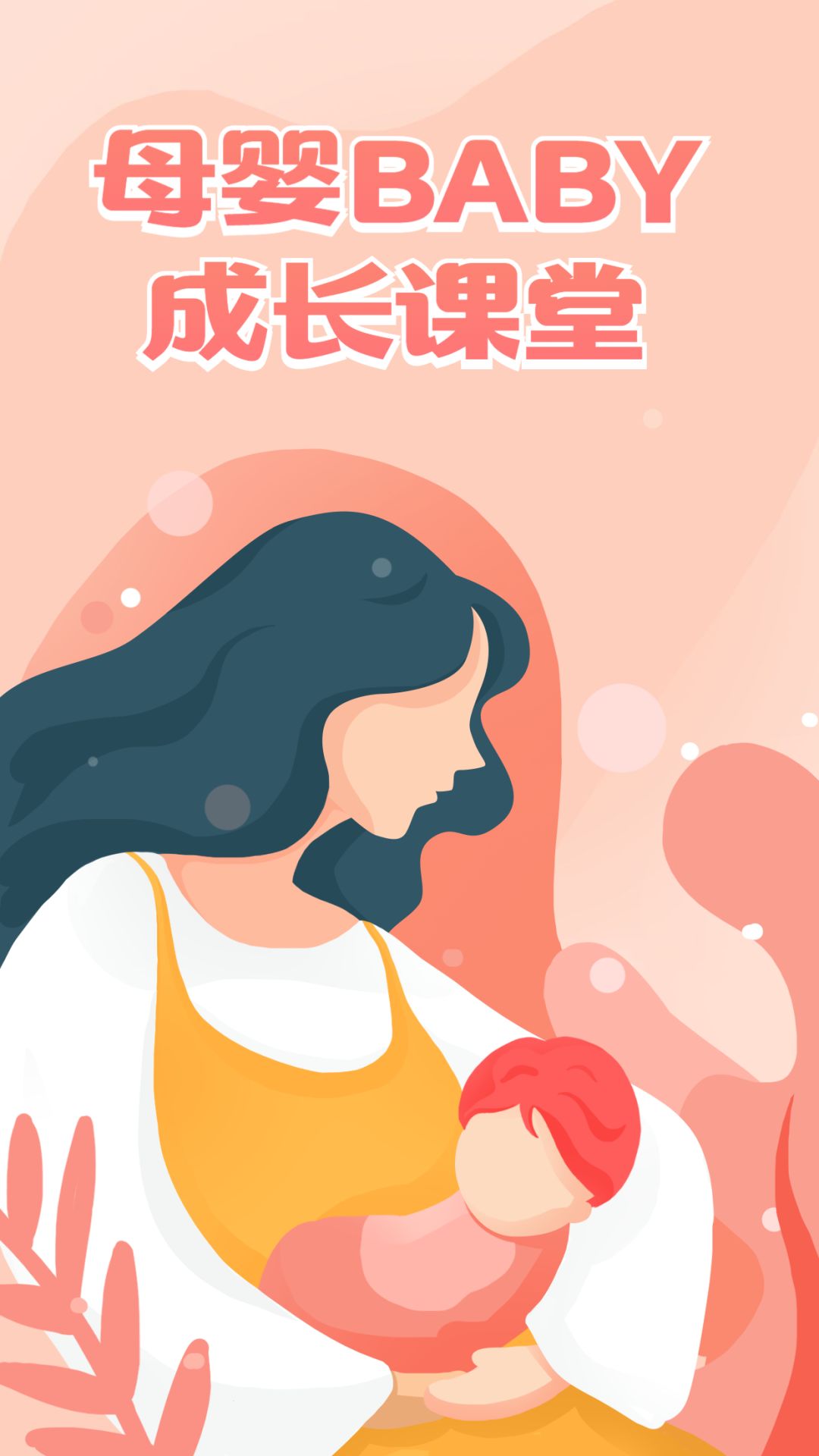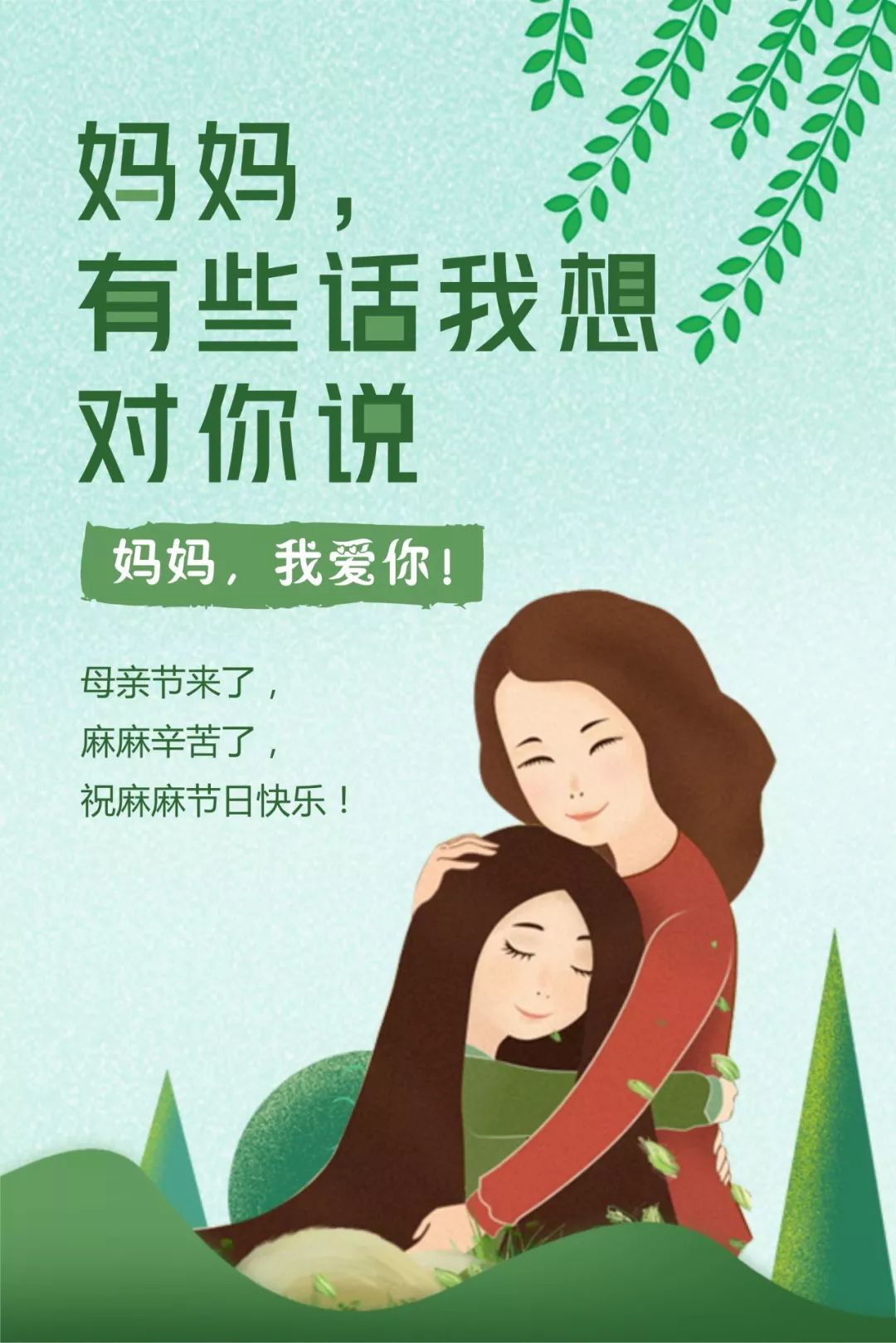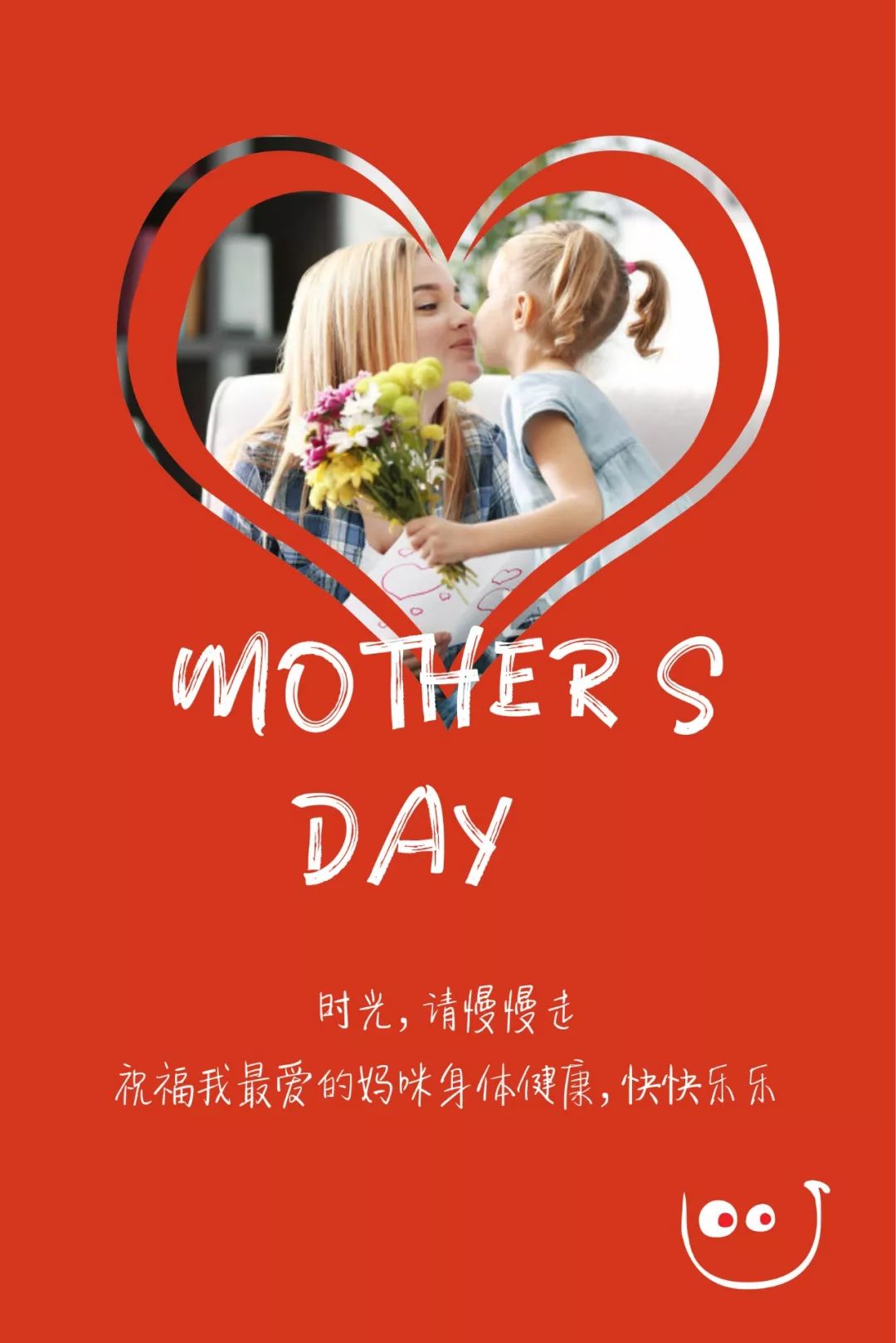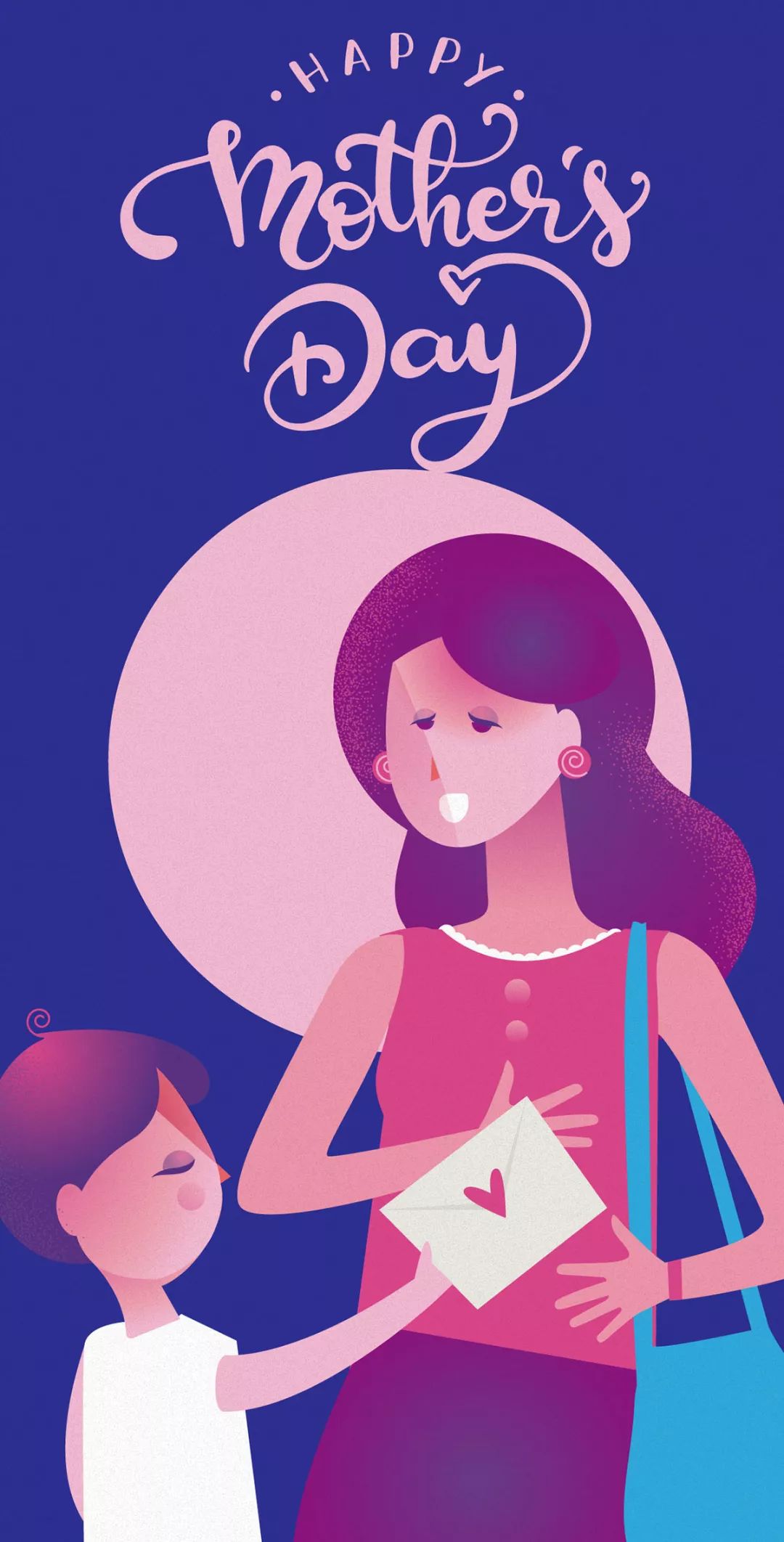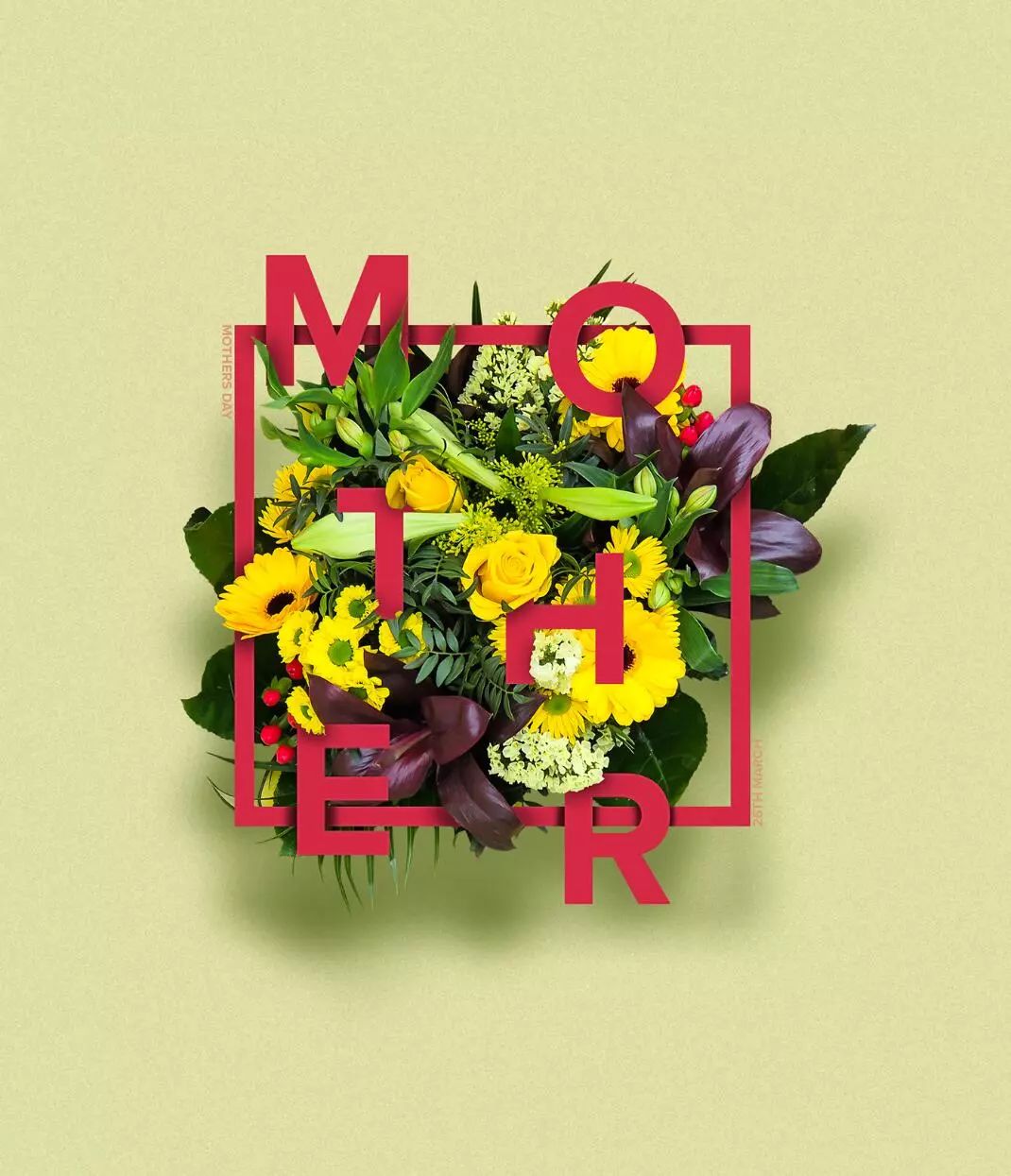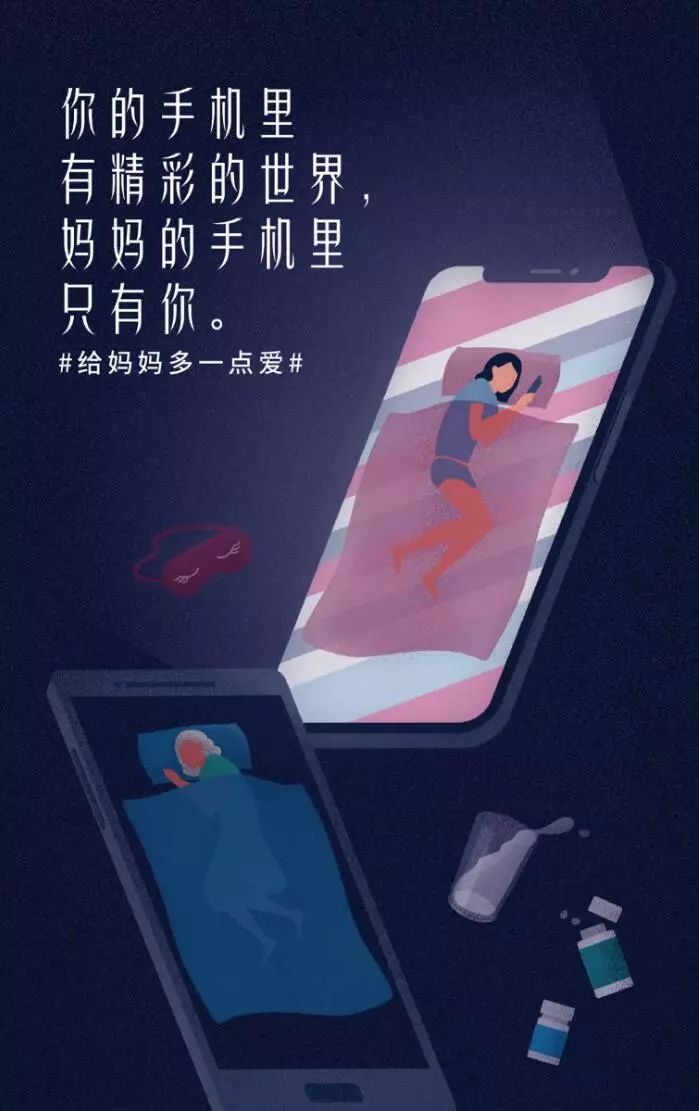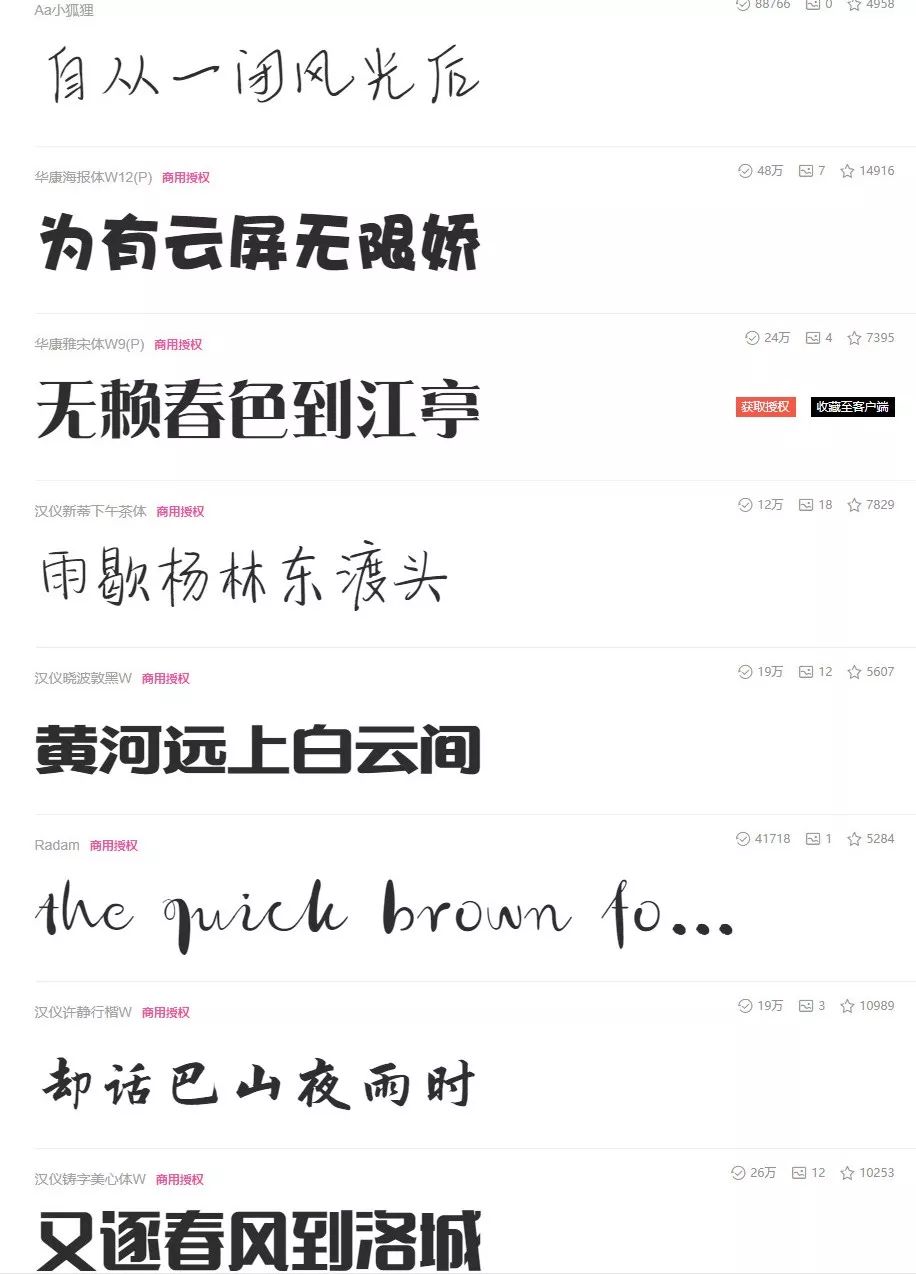
适合母亲节的字体分享,母亲节,用这些字体,发射你的小心心~
而偏圆润、端庄、手写的字体,更能表达对麻麻的爱意。
▲沐瑶软笔手写体
▲汉仪跳跳体
▲汉仪游园体
▲站酷庆科黄油体
▲杨任东竹石体
▲华康雅宋体
▲汉仪铸字美心体
▲汉仪雅酷黑+汉仪秀英体
▲汉仪菱心体
▲汉仪新蒂下午茶+Blinkstones
▲汉仪晓波敦黑
▲汉仪润圆
Mother's Day也可以有~